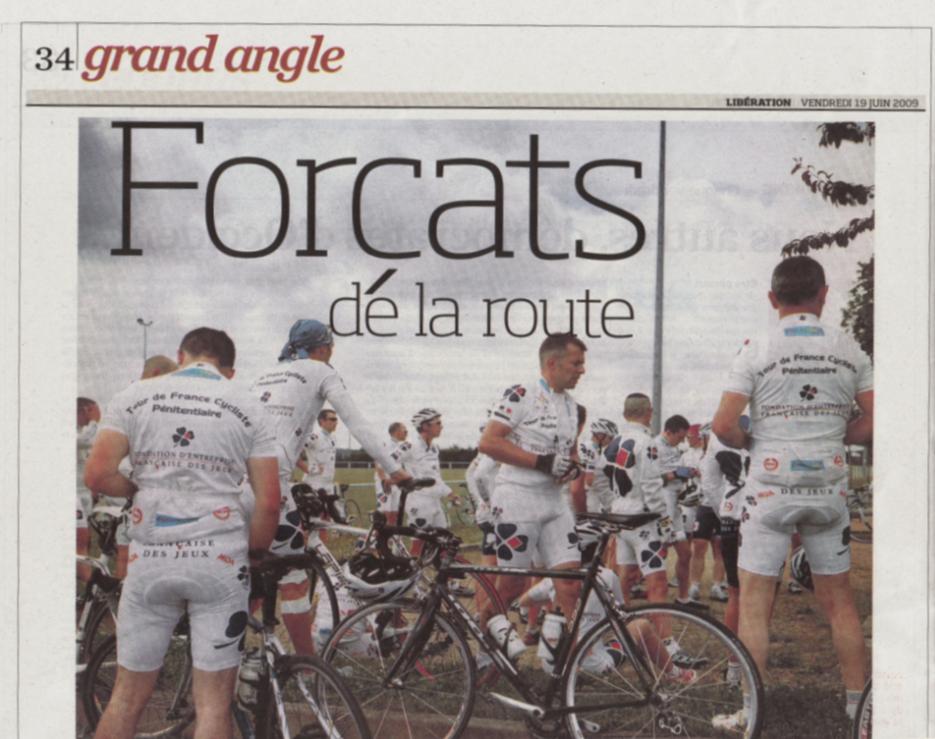
Message : Re: RE: [typo] Libé p34 (Jean-Marie Schwartz) - Lundi 22 Juin 2009 |
> Un coup de dé... > http://www.cetteadressecomportecinquantesignes.com/LibeFor.jpg Ouh ! qu'elle est moche, celle-là ! JMS